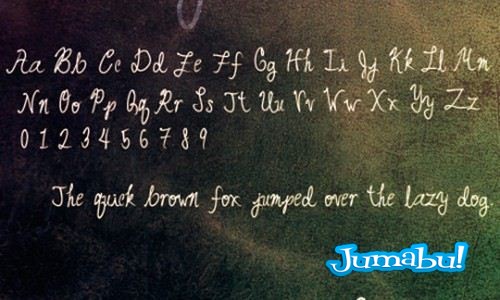
Novedades Tipografía Manuscritas para Descargar jumabu8 octubre, 2012 Nunca subí una tipografía pero esta me pareció que estaba bastante original. Si la quieren descargar es gratuita y está en muy buena calidad. Espero que les guste y que la disfruten! Saludos!!! fuente handwrite manuscrita tipografia Facebook Lanzará el Botón Quiero Manualidades Arma una Cajita para Regalos